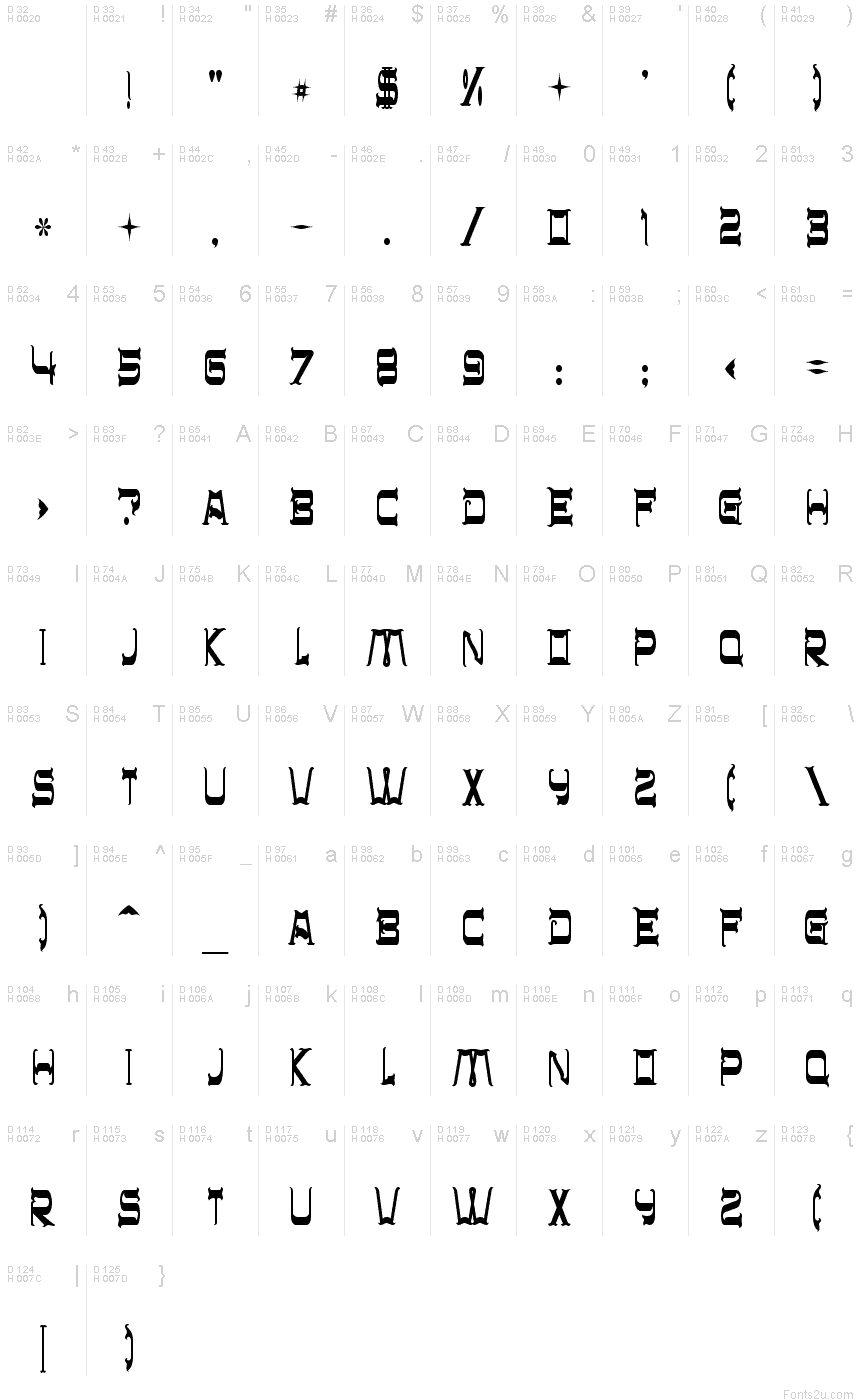
CHR32 من تصميم راي لارابي هو خط عرضي (Display) زخرفي مجاني يتميز بصورة ظلية ذات قرون لافتة للنظر، تمنحك مزيجاً بين الطابع الرقمي والنمط القوطي. تشكل السكتات السميكة التي تشبه الحبر أشكالاً كتلوية، ثم تتوهج فجأة لتتحول إلى منحنيات حادة تشبه الأنياب، مما يضفي على كل كلمة حضوراً ثقيلاً ومنحوتاً. الإيقاع ضيق ومدمج، لذا تبدو أسطر النص وكأنها شارات مستقبلية مطبوعة على معدن أسود بدلاً من مجرد حروف بسيطة.
باستخدام CHR32، ستحصل على ملمس جريء ومميز يعمل بشكل رائع لعناوين الألعاب، وأغلفة كتب الخيال العلمي، وملصقات الرعب، وشعارات الفرق الموسيقية، ومنشورات الفعاليات، ورسومات الملابس العصرية. يتألق هذا الخط المجاني عند استخدامه بأحجام كبيرة، حيث يمكن لتفاصيله المنحوتة ومساحاته السلبية غير المعتادة أن تتنفس. جرب إقران CHR32 بخط هندسي بلا زوائد (Sans Serif) نظيف للنصوص الداعمة، واجعل الخط الثانوي أصغر حجماً لتترك المجال للكلمة الرئيسية لتفرض سيطرتها.